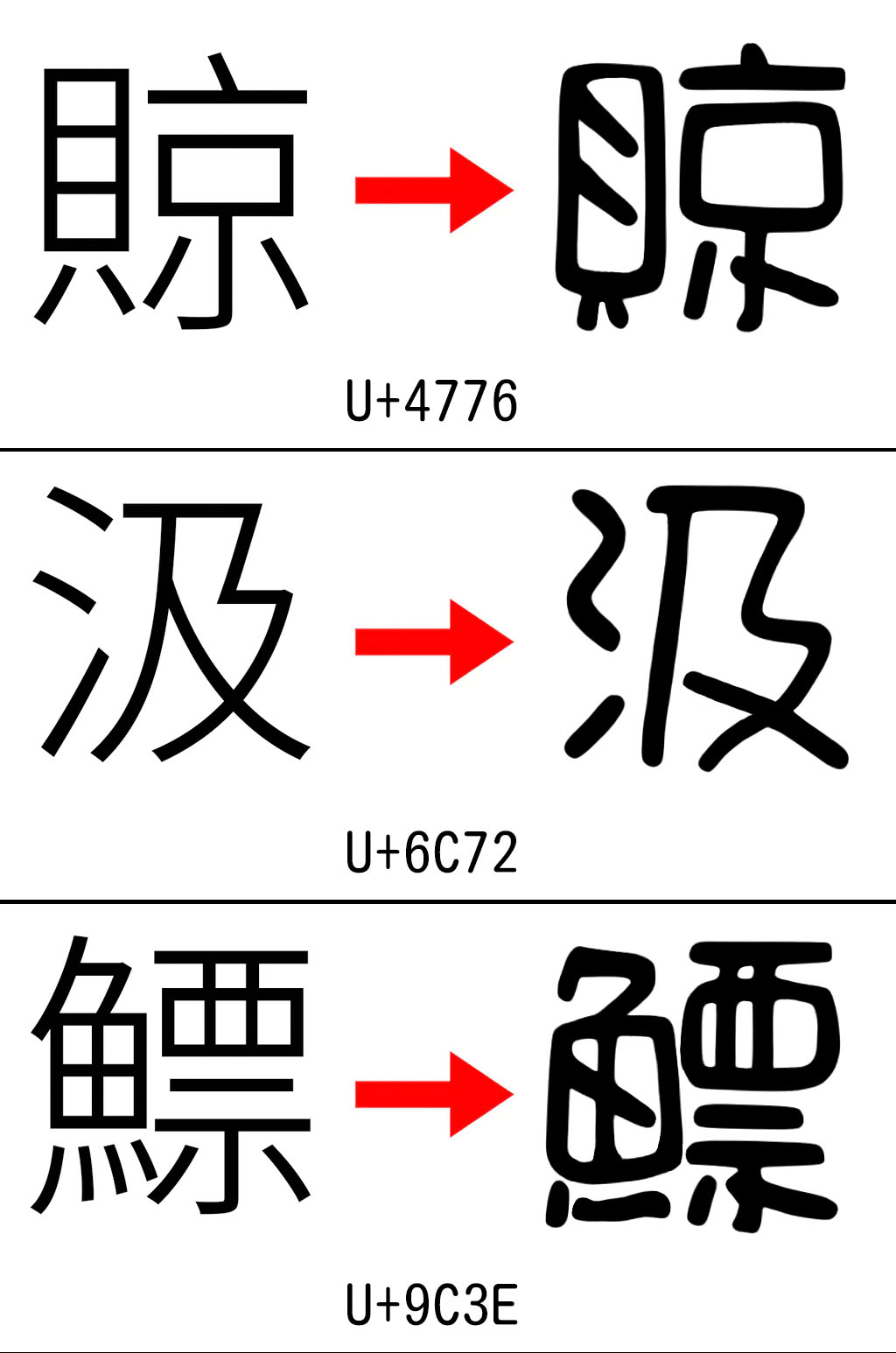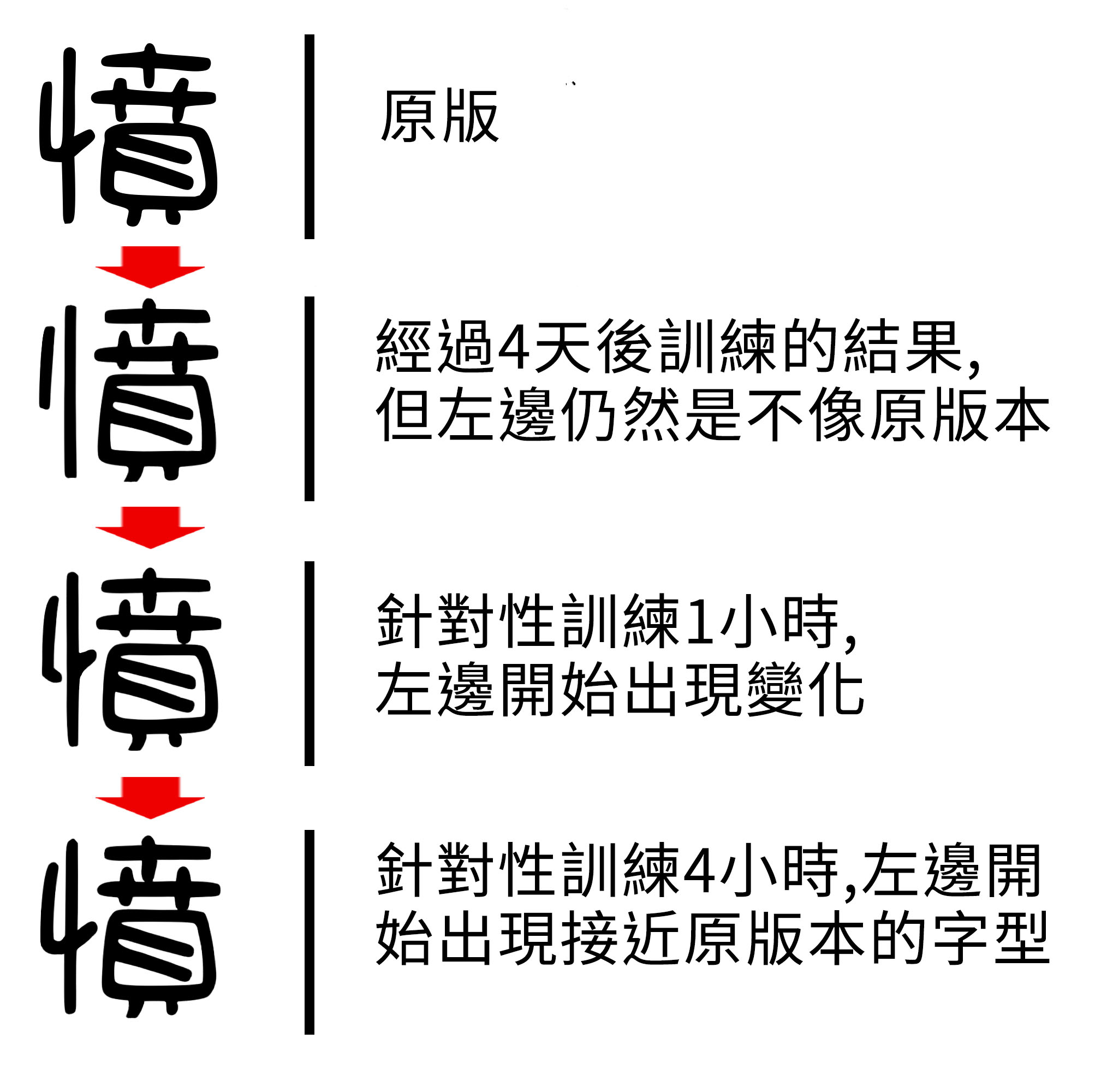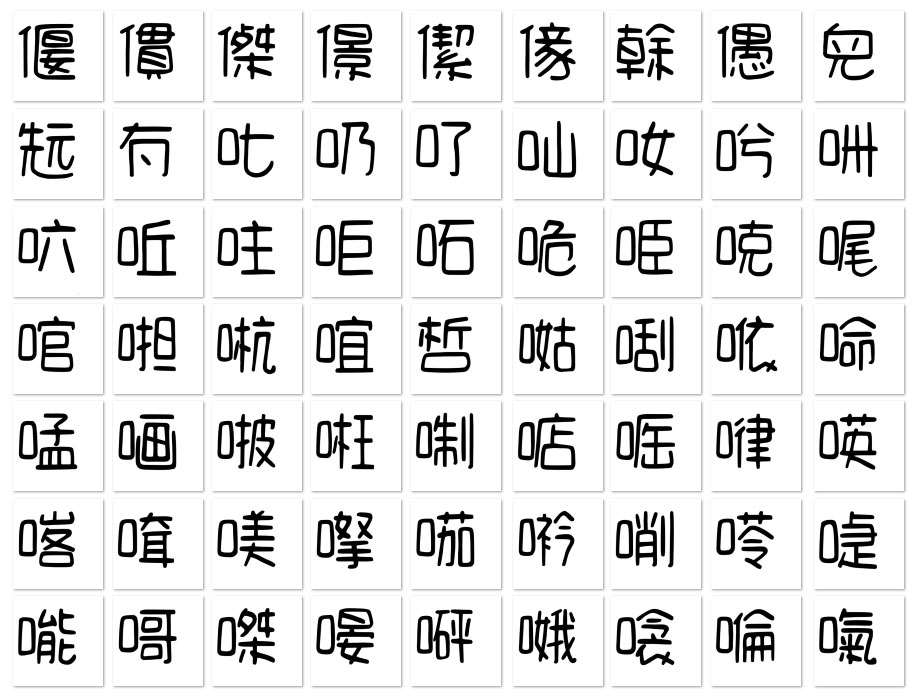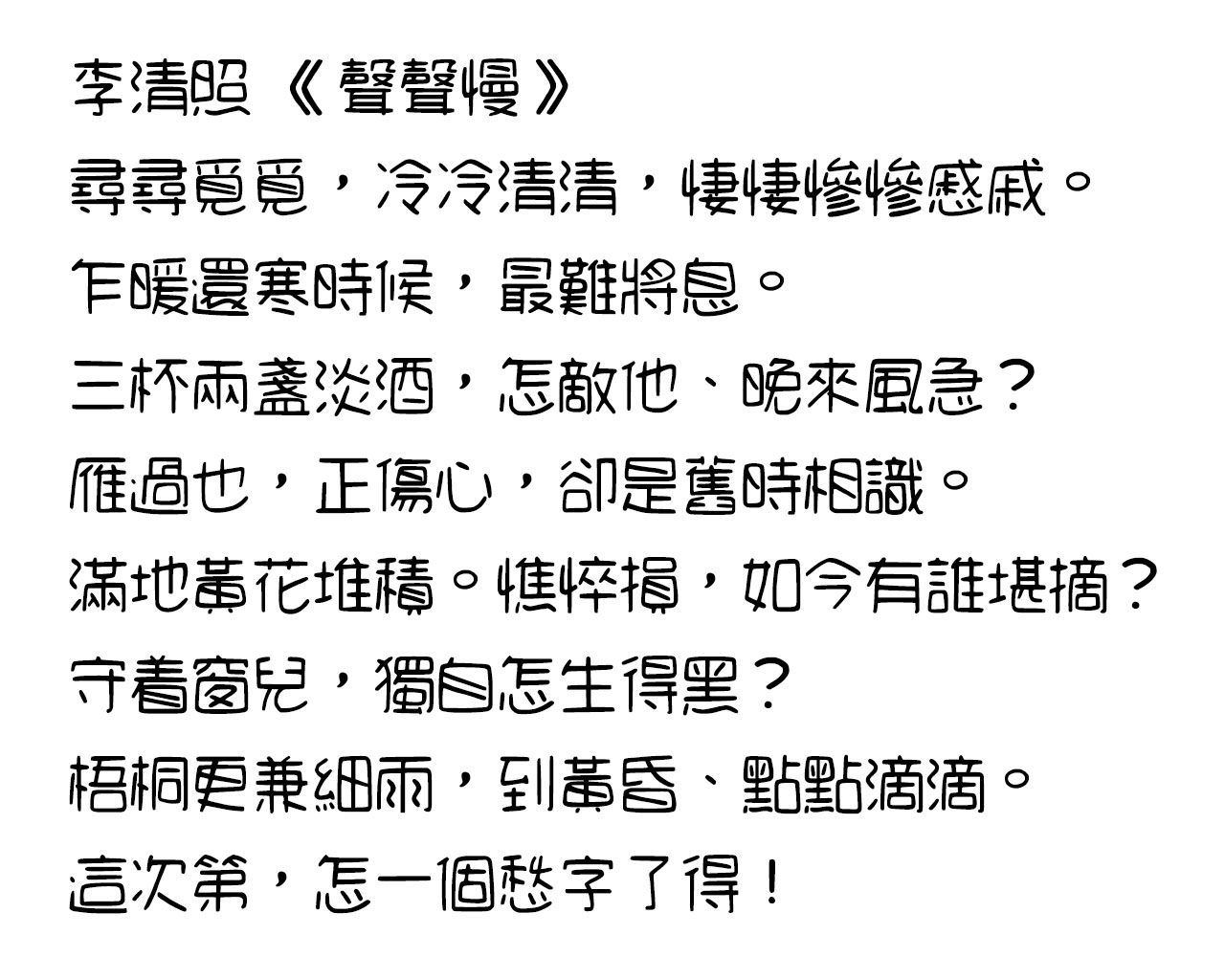
cjkFonts 手寫4 詳情頁
cjkFonts 手寫4 是基於 清松手寫體4 透過AI深度學習造字,原本清松手寫體4大約有4千幾百字,使用AI已造了2萬7千字,但因為要時間後期製作,現在只釋出大約1萬2千字,其餘的字待有時間才再加入。
由於是電腦學習了字型的特點及風格後,每個字根據學習後的數據造字,所以字體的風格會跟清松手寫體4有輕微的分別。
今次是1萬2千字的版本,大約用了2個月時間完成製作。清松手寫體4的風格跟一般字變化比較大,在整過訓練過程中,要反覆檢視結果,然後再訓練,再檢視,直至大部份的字型跟原版接近才能開始後期製作。
透過AI深度學習,字體轉換了風格。
反覆檢視結果,然後再訓練,再檢視。
cjkFonts 手寫4 的範例。
這些全部都是AI創作的字,清松手寫體4沒有這些字。
李清照《聲聲慢》
cjkFonts 手寫4